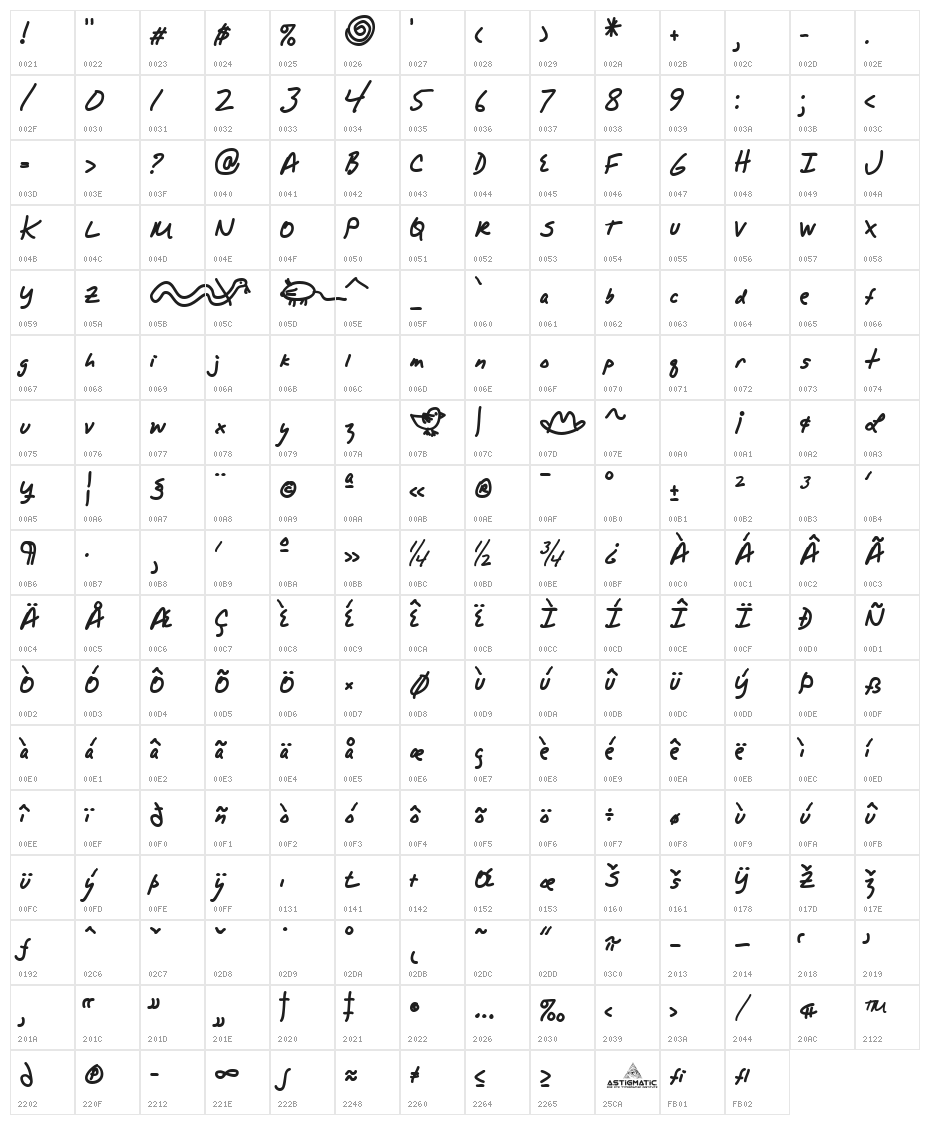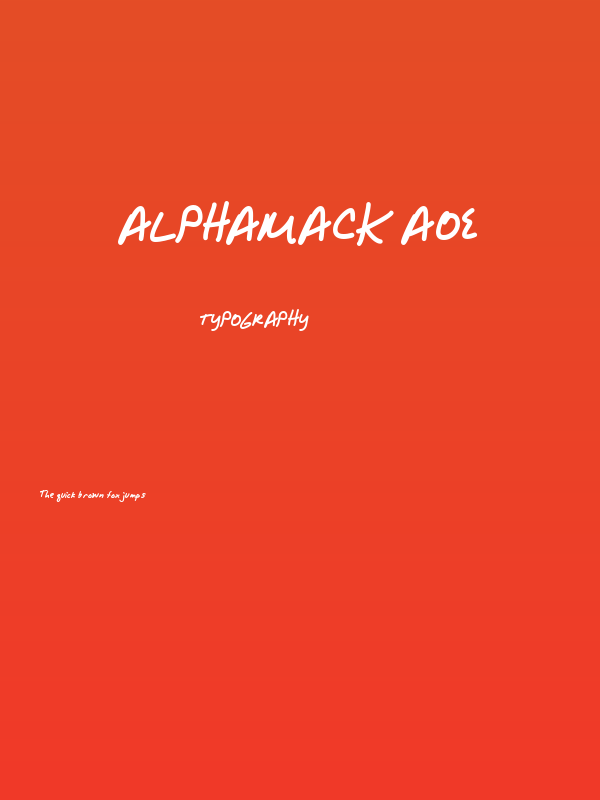
AlphaMack AOE Font
| Gesamtstil | Casual, Playful |
| Anwendungsfall | Logos, Headlines, Informal Invitations |
| Vorgeschlagene Projekte | Ideal for greeting cards, personal branding, casual posters, and social media graphics. |